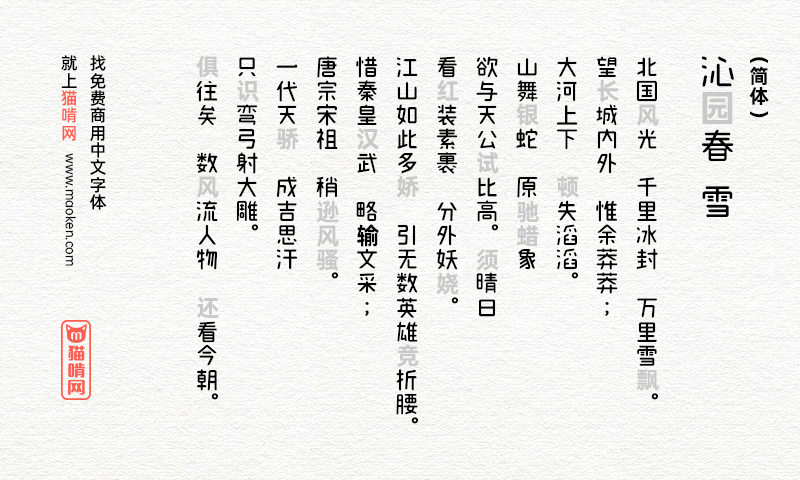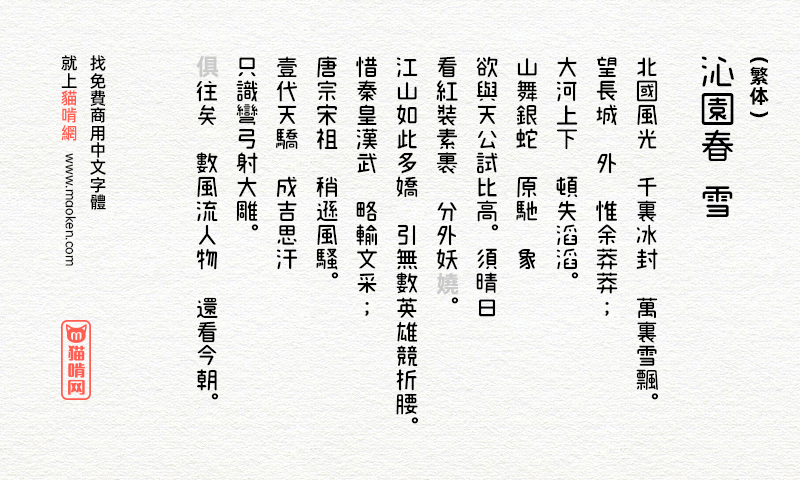
甜瓜体(マメロン):超甜超可爱免费的日文字体
字体名称:甜瓜体 マメロンPS中字体名称: マメロン Regular
这次来分享一款大家可能会喜欢的日文字体「 甜瓜体 」(日文名:マメロン),作者说应该叫做哈密瓜体。虽说这是一款日文字体,但是收录超过6,600个字 (JIS第1水准2965字,第2水准3390字) ,等于说支持灰常灰常多的中文字,而且用起来的样式可爱可爱的,一点都不输给 「 濑户字体 」 ,当然这还是取决于大家自己的喜好啦!如果喜欢这款字体就赶紧下载吧!